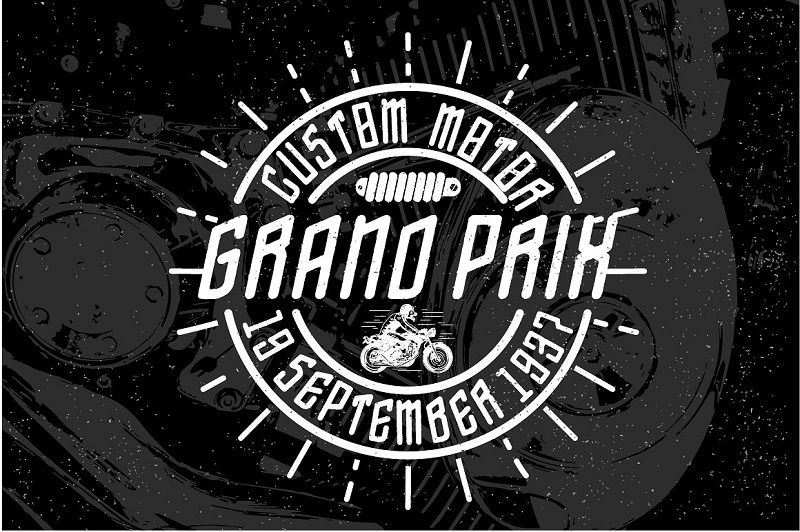
20 fuentes atrevidas con estilo de los años 70 de la década del cambio
La mayoría de la gente argumentará que la década de 1970 fue simplemente una extensión de la de los 60. Esos fueron realmente tiempos desafiantes, cuando hubo movimientos políticos, étnicos y ambientales masivos. Pero a pesar de las situaciones tumultuosas, todavía valía la pena recordar una década.
Quien podria olvidar The Brady Bunch, patines, Abba, y el Guerra de las Galaxias - todos los productos de los años 70. Disco Fever definitivamente estaba en racha en ese entonces, y casi todos los que conoces lucían un afro. No olvidemos el glam rock y el omnipresente Tupperware.
Otra marca de los 70 fueron los veranos calurosos. Jugar todo el día al aire libre, beber de una manguera, dormir en casa de un amigo durante días y construir fuertes en el patio trasero: de esto están hechos los recuerdos de la infancia.
¿Quieres revivir la década que lo cambió todo? Utilice sus habilidades creativas y estas fuentes de estilo de la década de 1970 para que los demás puedan vislumbrar el pasado.
Fuentes de estilo atrevido de los años 70
Vuelo
Cuente la Edad de Oro de los viajes con esta fuente de estilo de la década de 1970 que es perfecta para hacer boletos y hojas de trabajo. Limpio, elegante y funcional, este hará volar tu imaginación a primera clase.
Manicuore
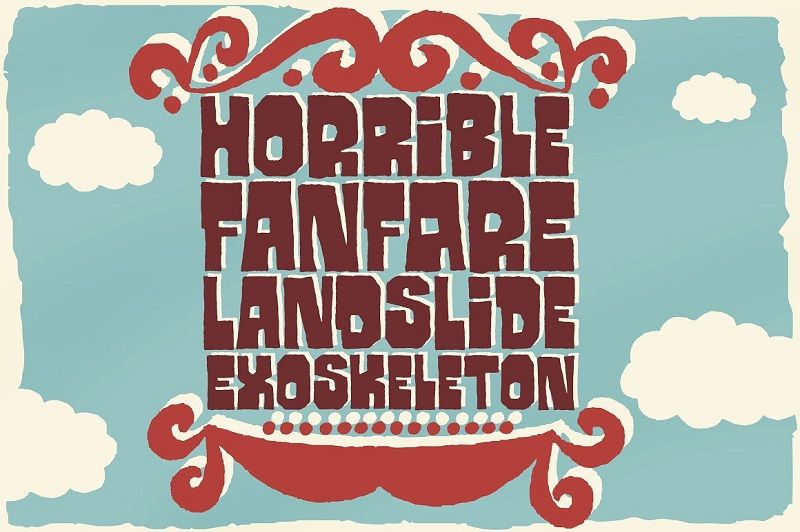
Este tipo de letra dibujado a mano está tomado de carteles de películas italianas por el prolífico cartel de la película artista Symeoni también conocido como Sandro Simeoni ). Con prácticas alternativas y 89 elementos gráficos, puede seguir creando diseños notables hasta altas horas de la madrugada.
Crocante
Ahora puedes recuperar esos atrevidos diseños de letras en mayúsculas de los modernos años 70 en este tipo de letra divertido y peculiar. Perfecto para alegrar el estado de ánimo o simplemente para mantener las cosas alegres.
Ziclets
¿Busca una fuente que sea atrevida, jugosa y totalmente extravagante? Esta fuente de estilo de la década de 1970 es definitivamente para personas de mente abierta como tú.
Pavo real de JAF
Simple y sin complicaciones, esto es para diseñadores modernos que solo necesitan hacer negocios. Sin pretensiones pero agradable a la vista, obtenga esta fuente y póngase manos a la obra.
Hora mágica de CA
Esta fuente de estilo de la década de 1970 le recordará los tiempos en que el Concorde volaba orgulloso en los cielos y los cócteles tenían un sabor increíble. Acelere sus proyectos descargando este sencillo tipo de letra hoy.
Kirimomi Swash
Aunque este tipo de letra de pantalla tiene sus raíces en los estilos clásicos, los bordes afilados le dan suficiente actitud para destacarse del ruido. Funcionalmente elegante pero también orgullosamente estético, deja que esta hermosa fuente cuente tu historia al mundo.
Calista
Inspirado en las obras de Francois Boltana a principios de la década de 1970 y los de Milka Peykova a finales de la década de 1970, esta fuente es perfecta para encabezados y diseños de logotipos que exigen atención.
SOLID70
Esta fuente equilibrada de estilo de los años 70 es perfecta para artistas que buscan crear diseños asombrosos con solo unos pocos clics. El estilo elegante engañará a cualquiera que te haya llevado horas hacer, pero nadie tiene que saber tu secreto.
Funkydori - Negrita
¿Es posible combinar los estilos funky de los años 70 con el ambiente moderno de hoy? Este tipo de letra dice que puedes. Disfruta de las elegantes formas de las letras realzadas con extravagantes mayúsculas, alternas y finales.
Addington CF Steadfast Serif
Tal vez no te gusten todas esas fuentes frescas y originales de los años 70, pero aún quieres algo similar en caso de que lo necesites. La solución: este encantador serif con el que se puede contar tanto para obras de arte tradicionales como para proyectos más elegantes.
Cooper Black Swash
Creada en el espíritu del trabajo de Oz Cooper, esta fuente de estilo de la década de 1970 quedaría genial en cualquier obra de arte moderna o digital.